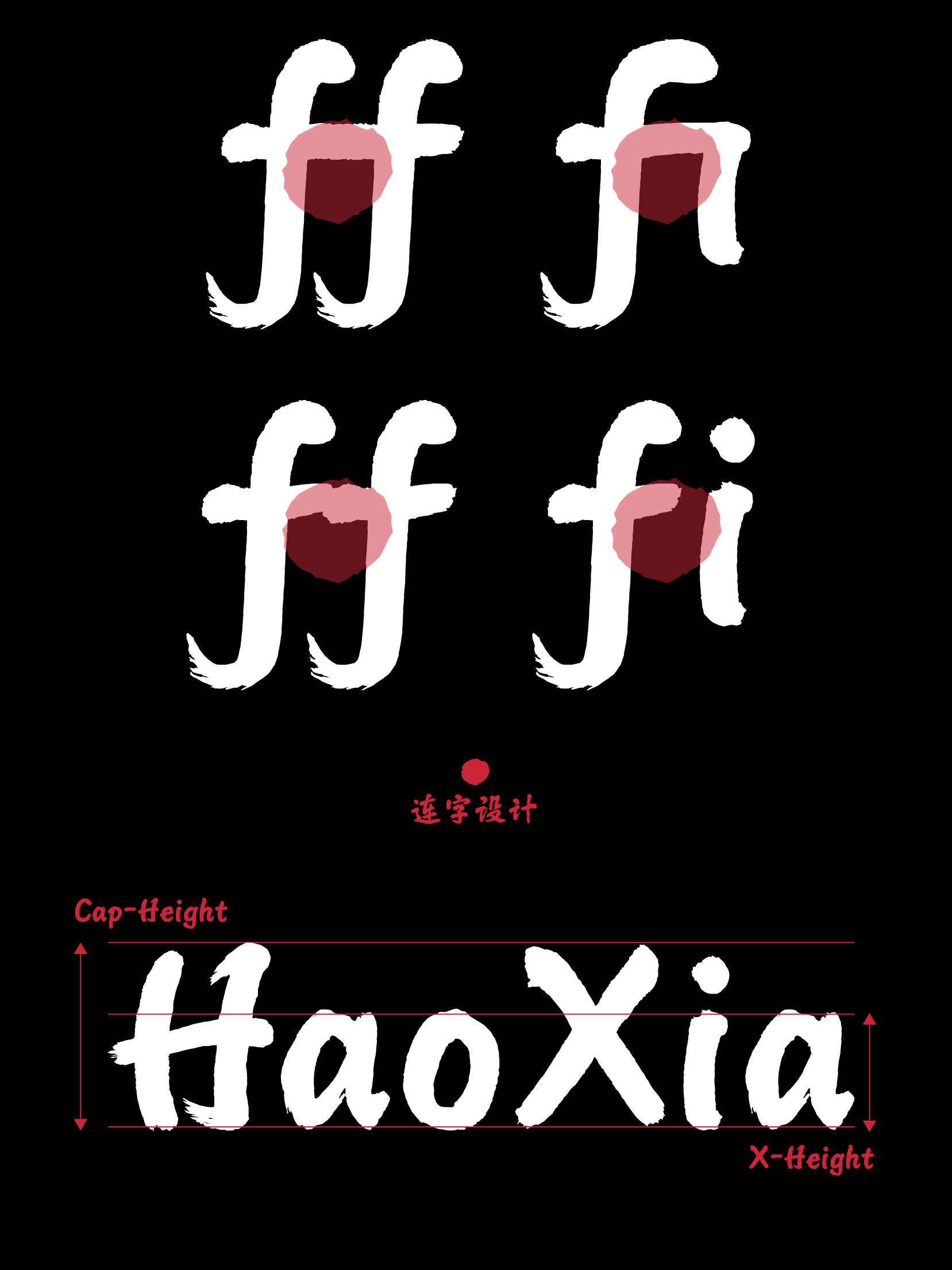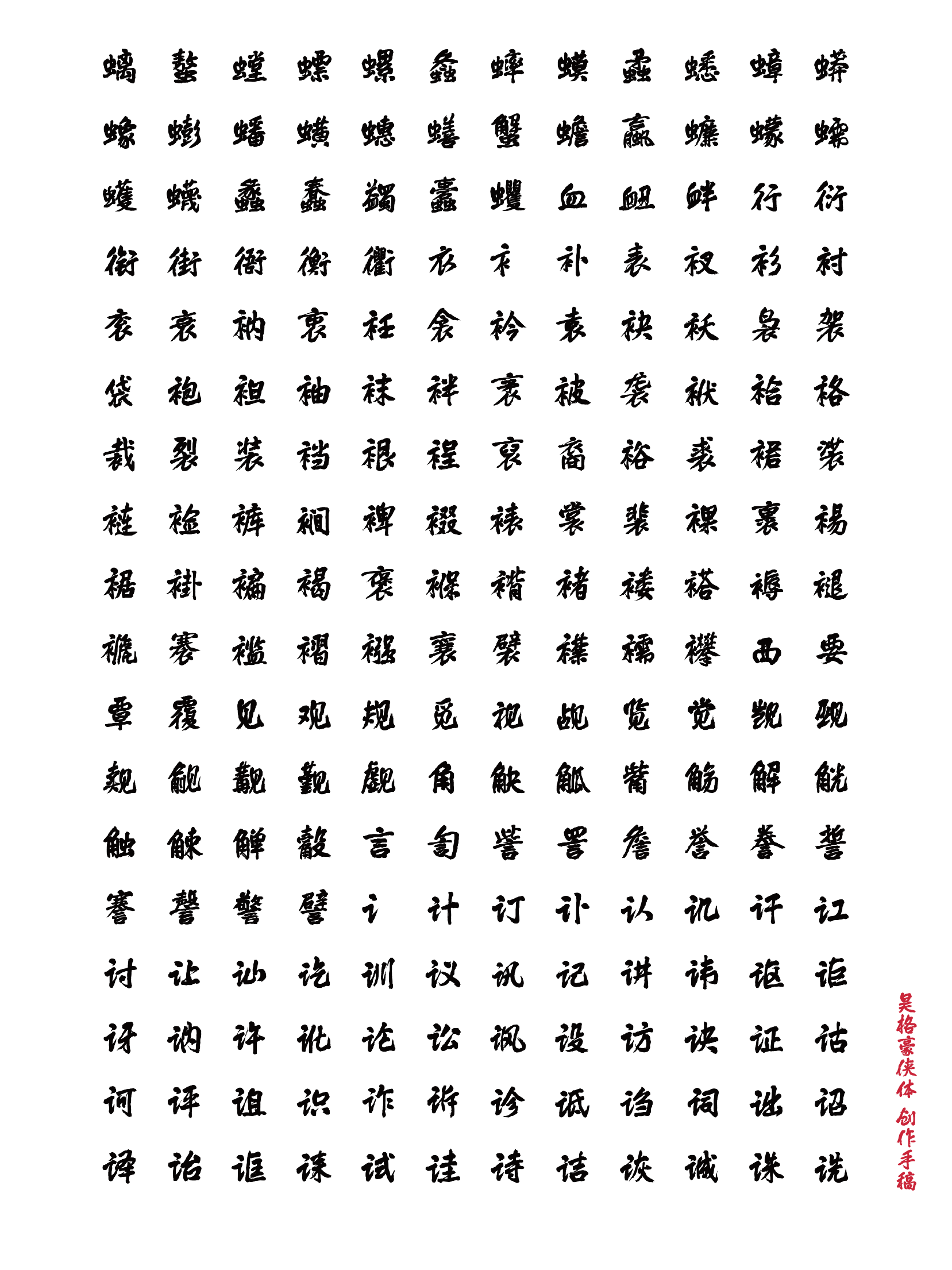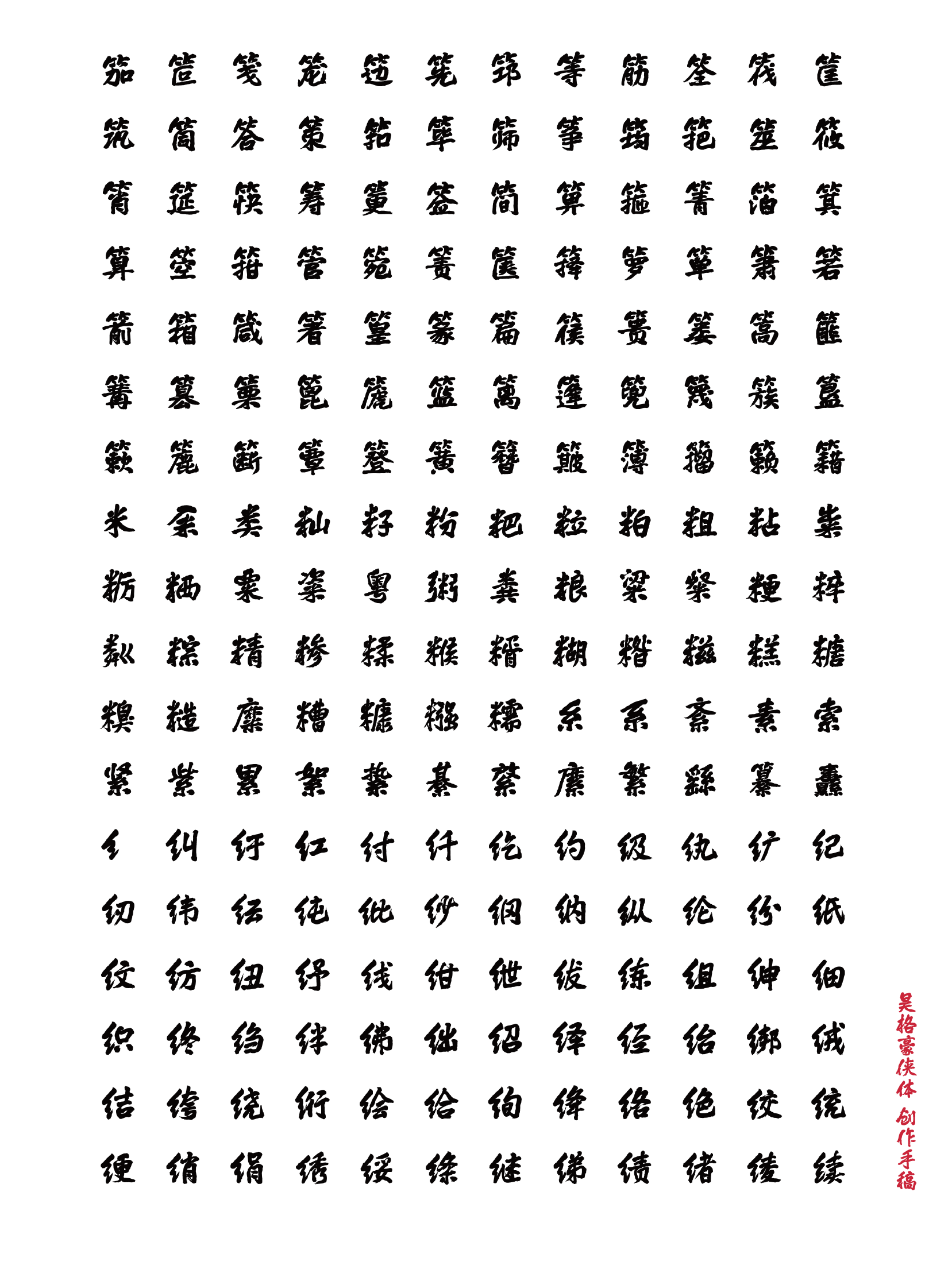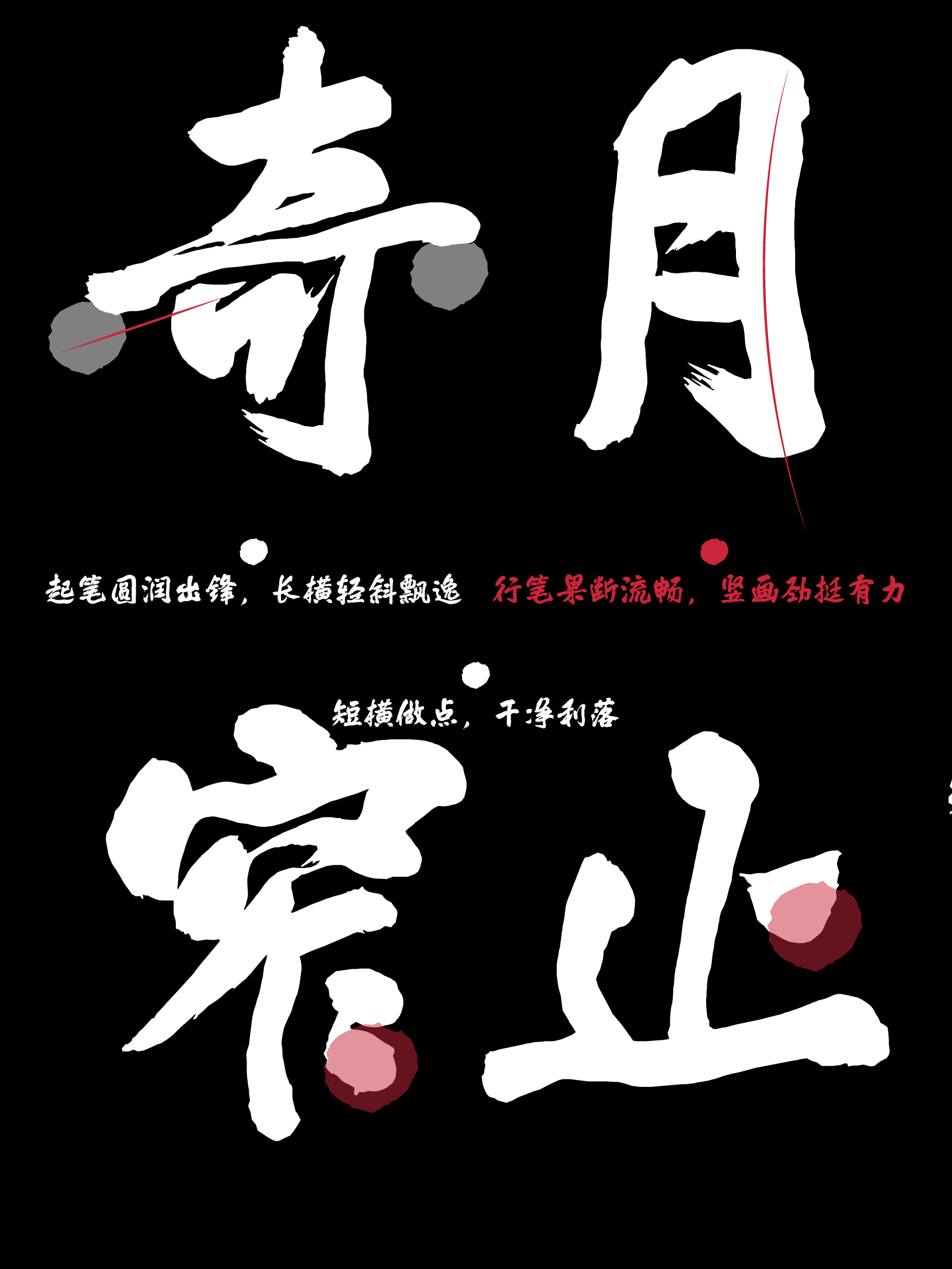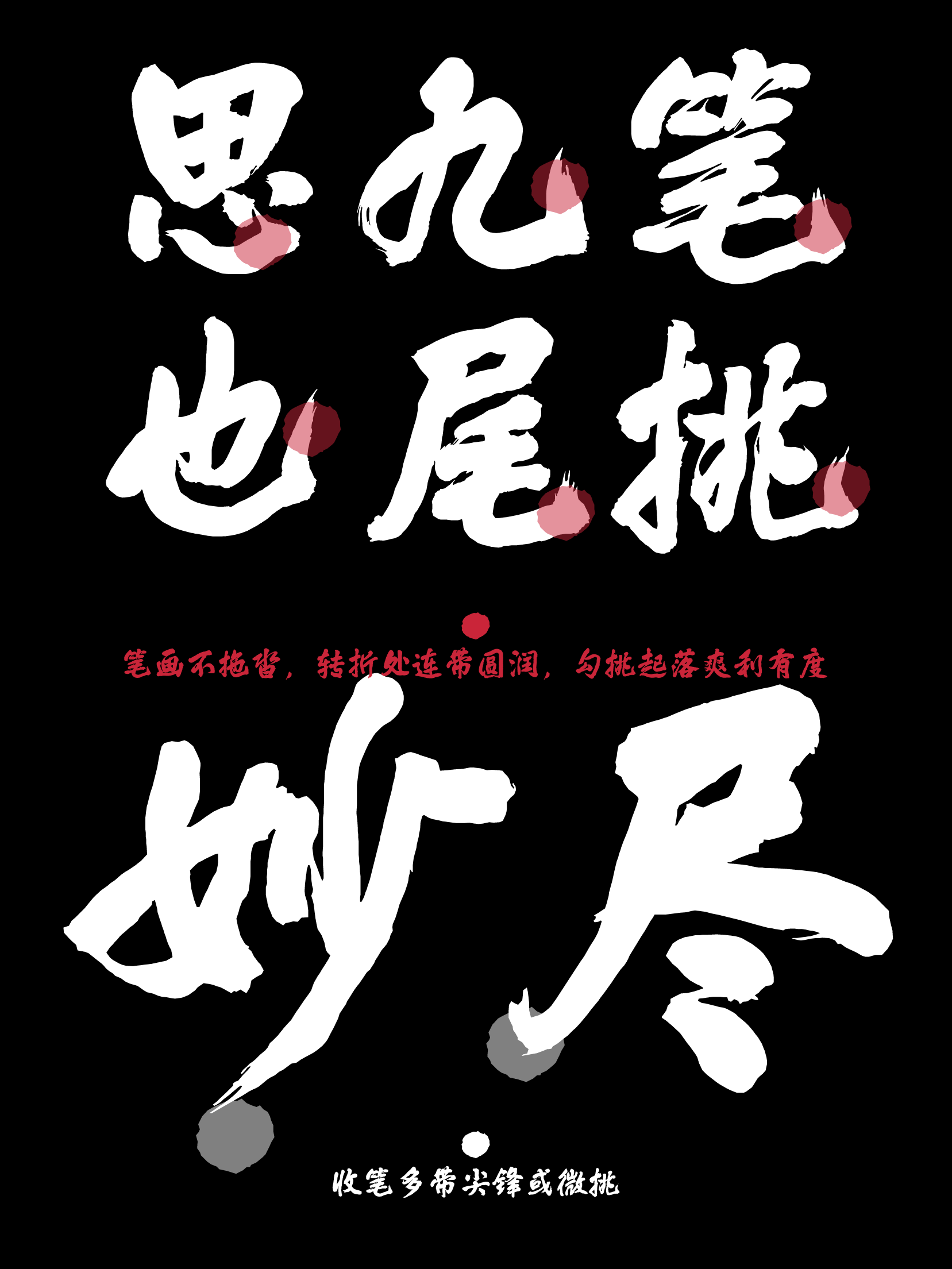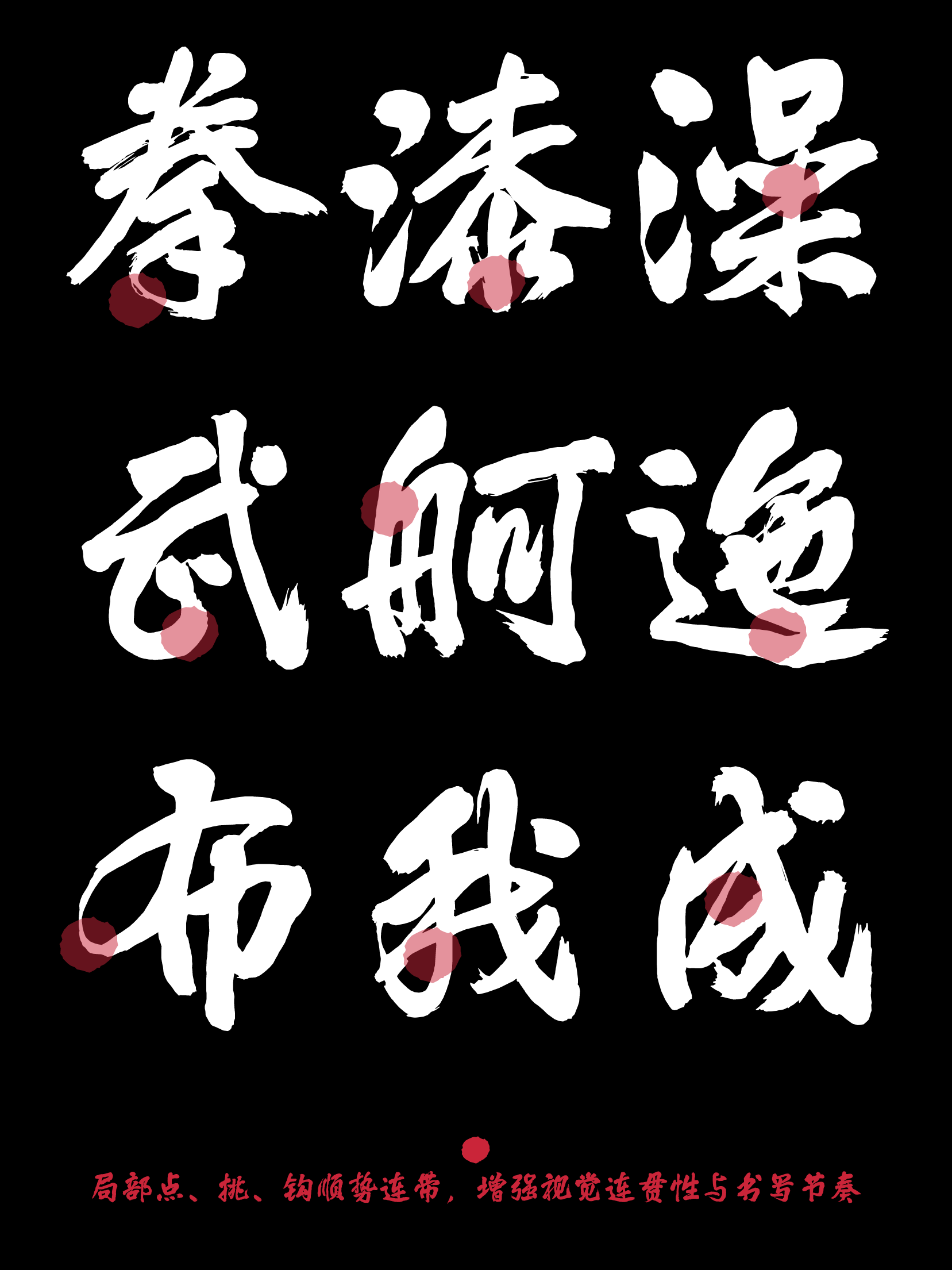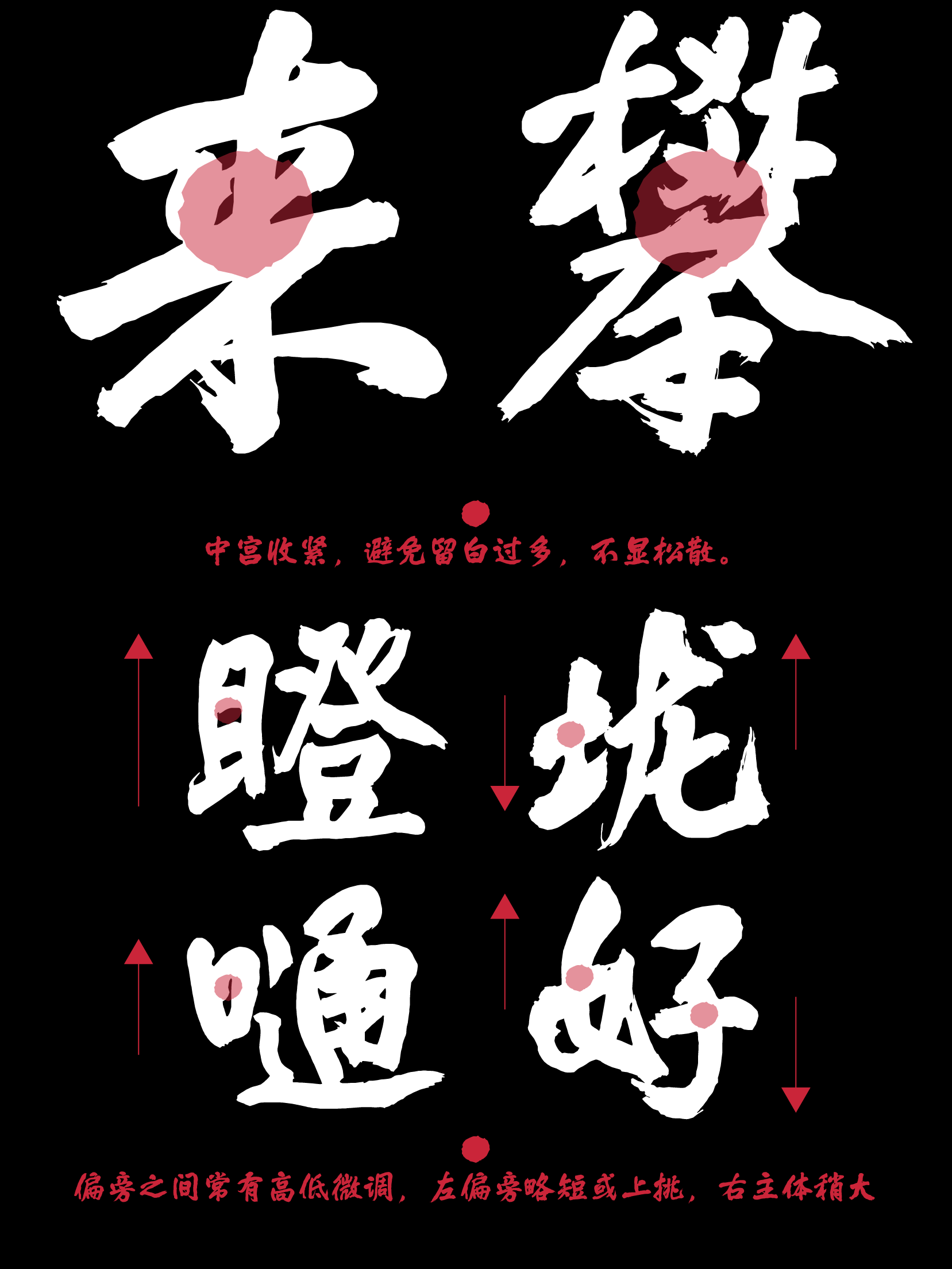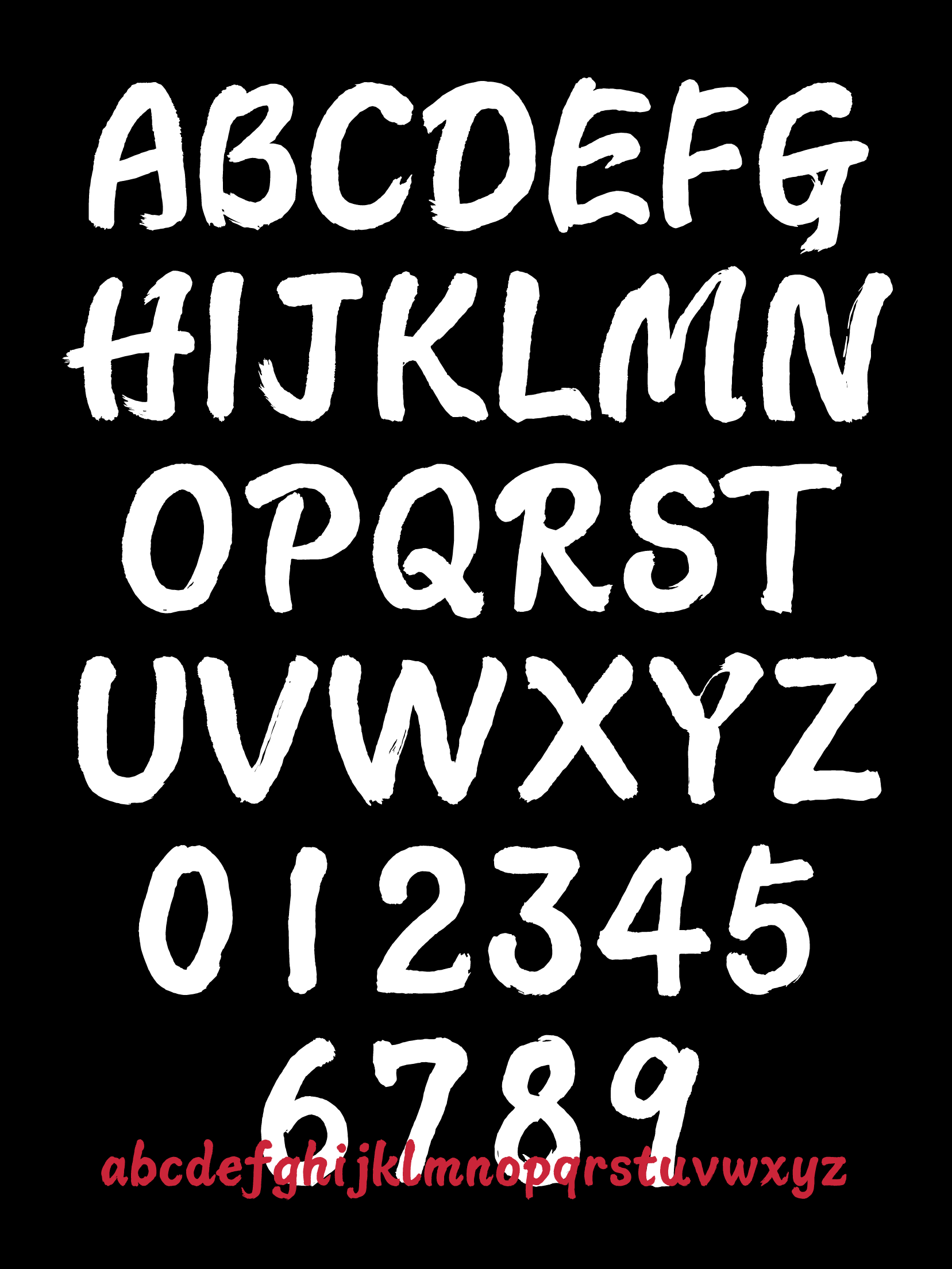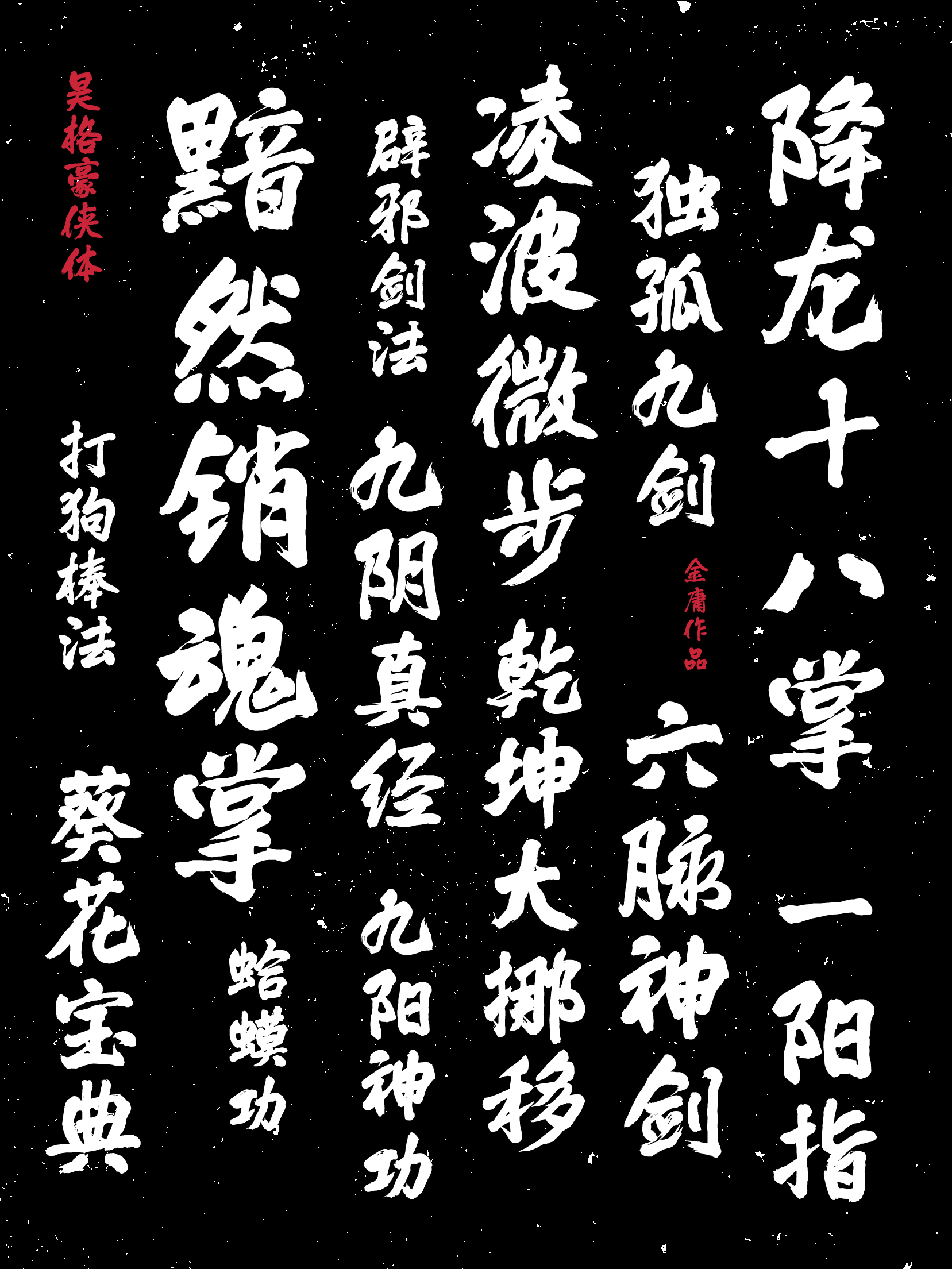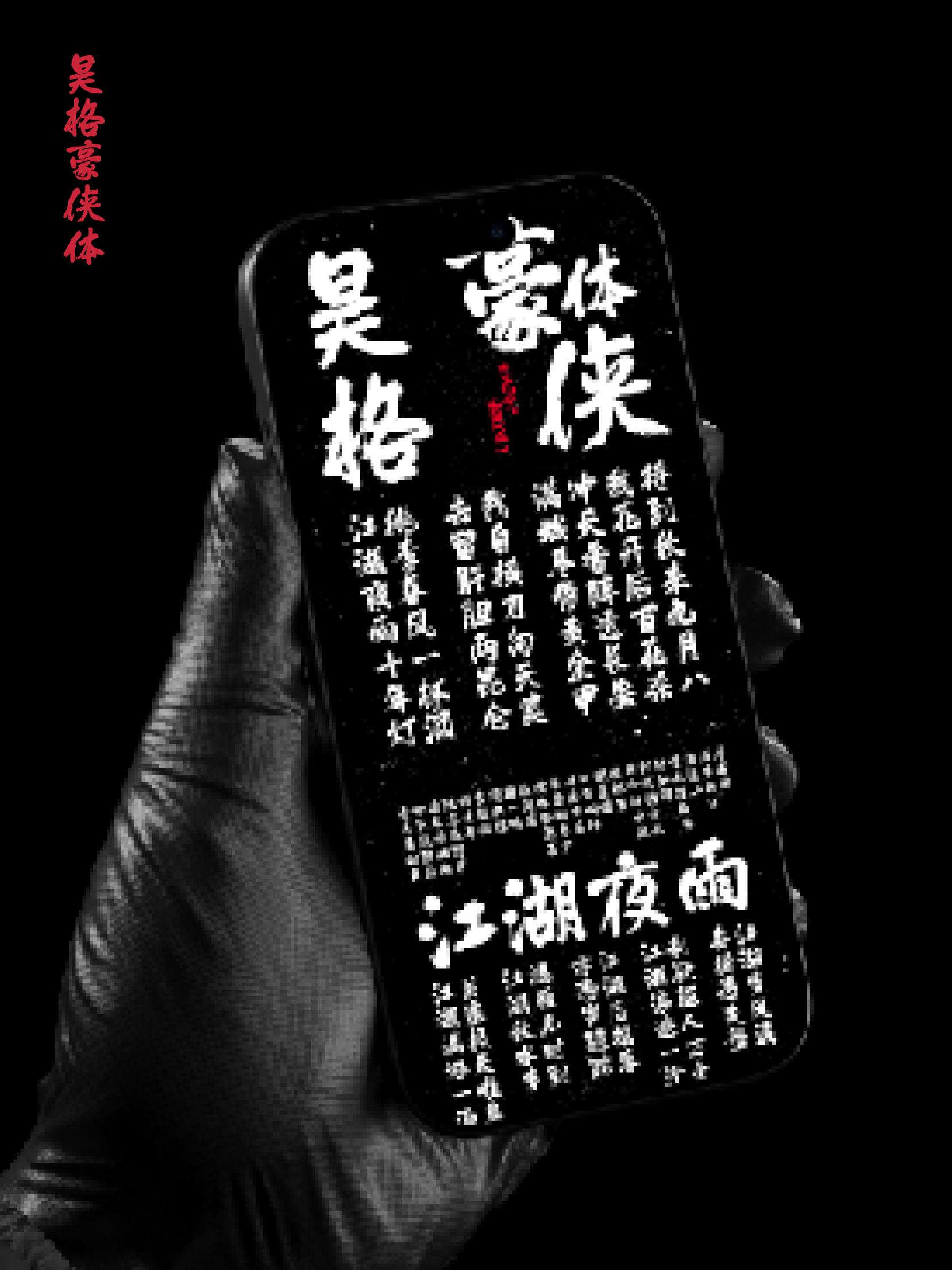
昊格豪侠体
昊格豪侠体,潇洒恣意,豪迈有力,昊格豪侠体是一款书写感强烈,动静相宜的书风字体。结构上,以楷书为筋骨,中宫紧收,左右部件高低错落,左偏旁上挑略短,右主体略大,整体布势稳中带动,呈现出清晰而富有节奏的空间秩序;笔形上,起笔圆润出锋,行笔果断流畅,长横轻斜飘逸,竖画劲挺有力,短横做点干净利落,展现出豪侠式的刚柔并济;细节上,撇捺点多带顺势尖锋或圆钩,笔画不拖沓,转折处连带圆润,勾挑起落爽利有度,动感十足;在楷书基础上融入少量行书意趣,局部点,挑,钩顺势连带,增强视觉连贯性与书写节奏,字面饱满密实而不板滞;整体风貌自如潇洒,兼具骨力与神采,正如江湖豪侠,外形随性,内蕴沉着。
类      型:书法